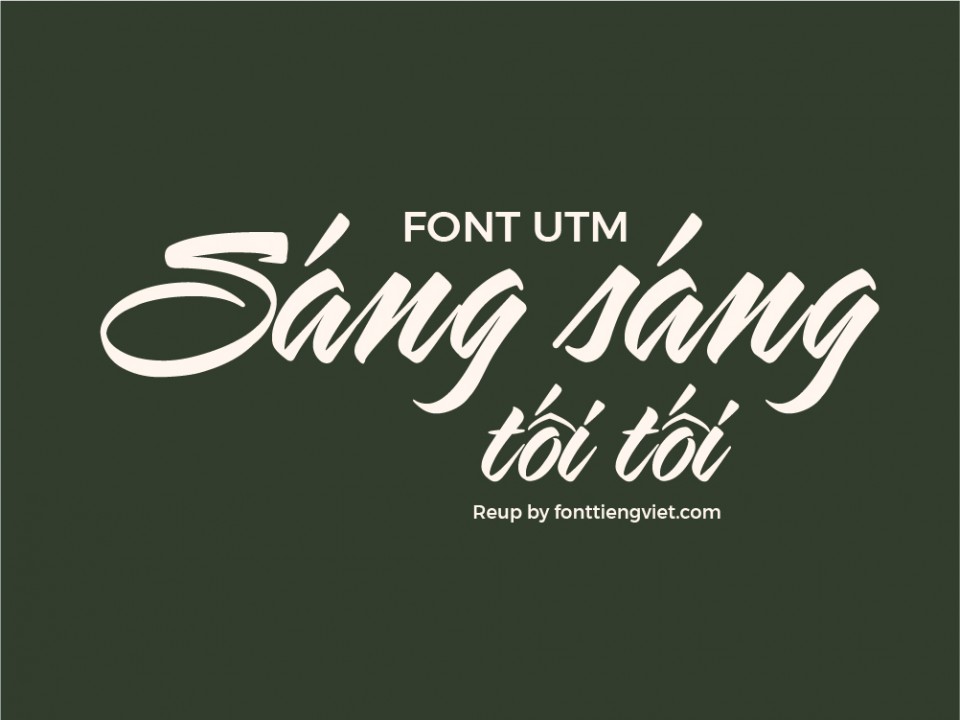
Font việt hóa UTM Sarah
Font việt hóa UTM Sarah là một trong những bộ phông chữ thuộc dòng Script mềm mại được cộng đồng thiết kế tại Việt Nam ưa chuộng. Với đường nét uyển chuyển và thanh lịch, bộ Font Miễn Phí này mang đến hơi thở hiện đại nhưng không kém phần cổ điển cho các tác phẩm đồ họa. Đối với các bạn học sinh và giáo viên, việc sử dụng phông chữ này giúp các bài thuyết trình hay tài liệu học tập trở nên sinh động và lôi cuốn hơn rất nhiều.
Đặc điểm nổi bật của Font việt hóa UTM Sarah
Thiết kế mềm mại và linh hoạt
Đặc trưng lớn nhất của bộ phông này chính là những nét chữ uốn lượn tự nhiên giống như chữ viết tay. Điều này tạo cảm giác gần gũi và thân thiện cho người xem. Các ký tự được tinh chỉnh kỹ lưỡng để đảm bảo hiển thị rõ ràng trên cả màn hình máy tính lẫn bản in, giúp người dùng dễ dàng ứng dụng vào nhiều mục đích khác nhau từ trang trí bìa sách đến làm thiệp mời.
Khả năng hiển thị tiếng Việt hoàn hảo
Khác với các bộ phông chữ nước ngoài thường bị lỗi dấu khi gõ tiếng Việt, phiên bản này đã được xử lý trọn vẹn về mặt mã hóa. Bạn có thể yên tâm sử dụng mọi ký tự đặc biệt của tiếng Việt mà không lo hiện tượng mất chữ hay sai lệch định dạng. Điều này cực kỳ quan trọng trong môi trường giáo dục khi cần sự chính xác tuyệt đối về ngôn ngữ.
Ứng dụng Font việt hóa UTM Sarah trong thực tế
Người dùng có thể khai thác bộ phông này cho các dự án sáng tạo như thiết kế tiêu đề bài giảng, làm báo tường hoặc trang trí ảnh kỷ yếu. Sự kết hợp giữa nét chữ nghệ thuật và tính ứng dụng cao giúp tác phẩm của bạn luôn chuyên nghiệp. Hãy tải ngay tại Font Miễn Phí, Font Việt Hóa, Font việt hóa UTM Sarah để trải nghiệm sự khác biệt. Hy vọng bài viết giúp bạn hiểu rõ hơn về giá trị mà bộ phông này mang lại cho cộng đồng yêu thiết kế.